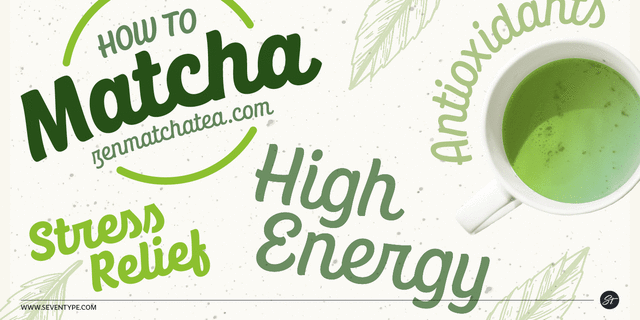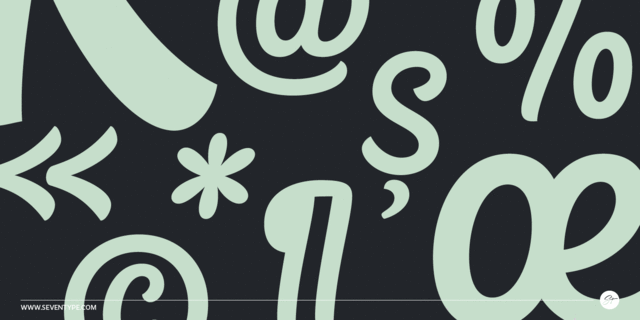
На создание шрифта CoolKids нас вдохновила песня «Signs of Life» группы Arcade Fire. Так как в песне поётся про крутых детей, мы задались вопросом как бы мог выглядеть шрифт с таким названием. Мы сразу же поняли, что он должен быть расслабленным и в то же время решительным, выделяться из толпы.
После жирного начертания мы решили добавить светлую, обычную и среднюю насыщенности, чтобы расширить возможности для вашего дизайна.
CoolKids имеет начальные и конечные альтернативы, которые появляются автоматически. Это придает шрифту более естественный вид, делает его похожим на рукописный.
Каждый символ был старательно нарисован, а соединения по-настоящему плавные.
Это шрифтовое семейство говорит на большинстве языков, в которых используются латинские символы. Как в основных, так и в альтернативных формах.
CoolKids прекрасно подходит для создания логотипов, дизайна упаковки, постеров и многого другого.
Шрифт разработали Луис Бандовас и Витория Невес в 2019 году.